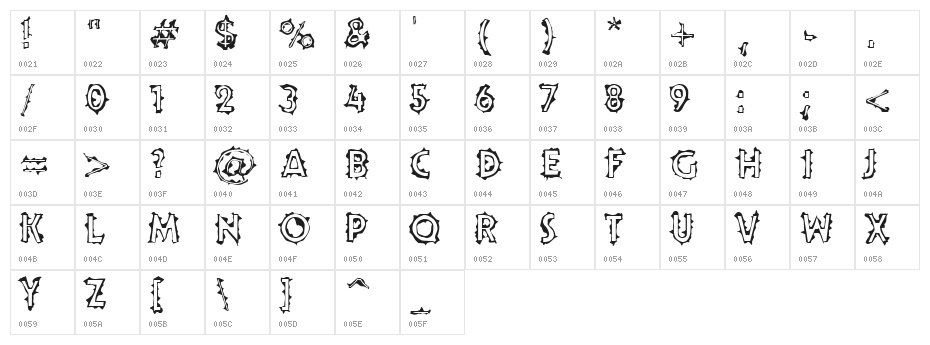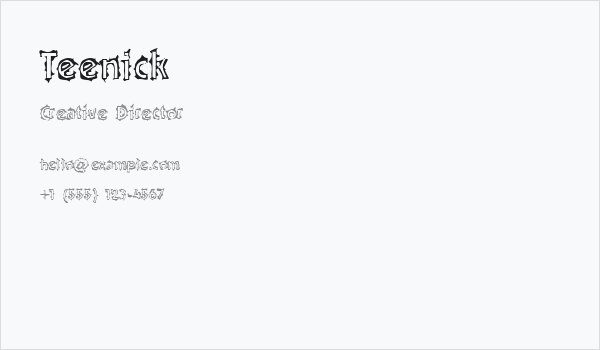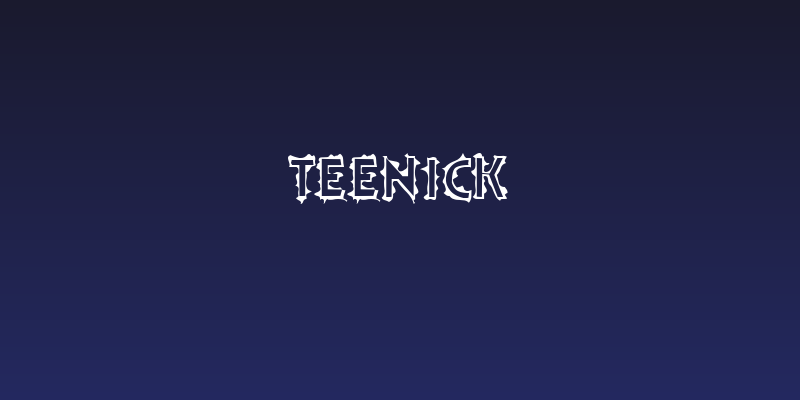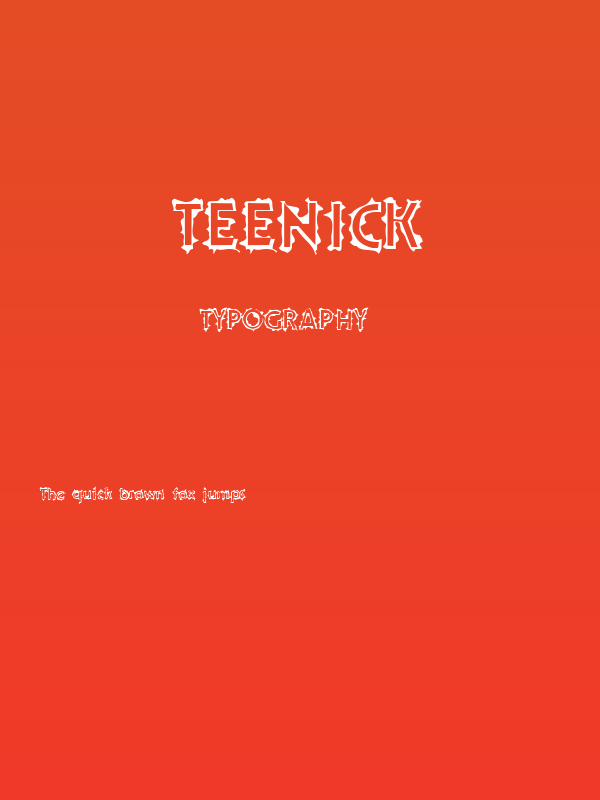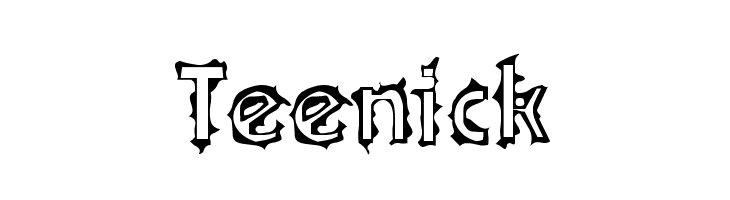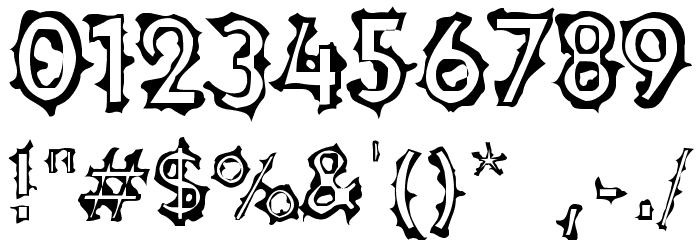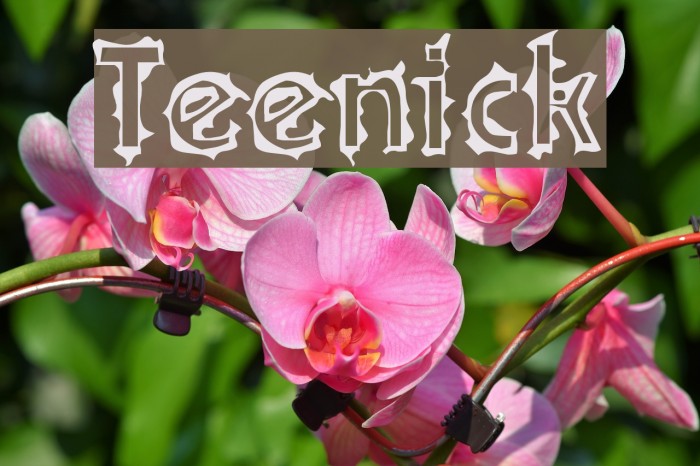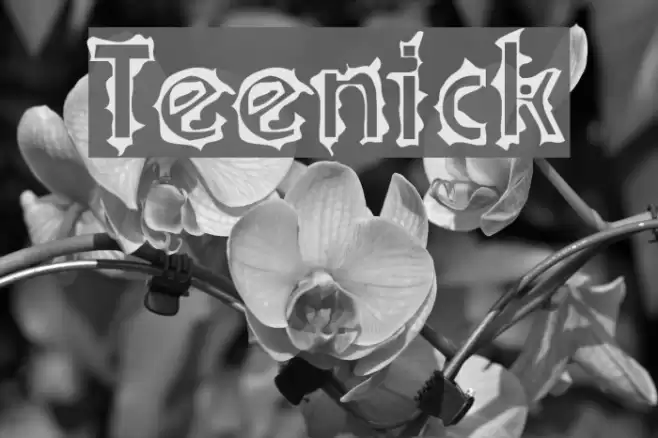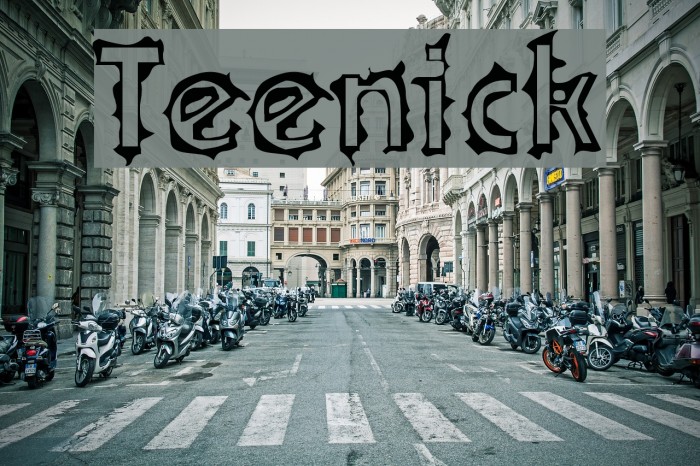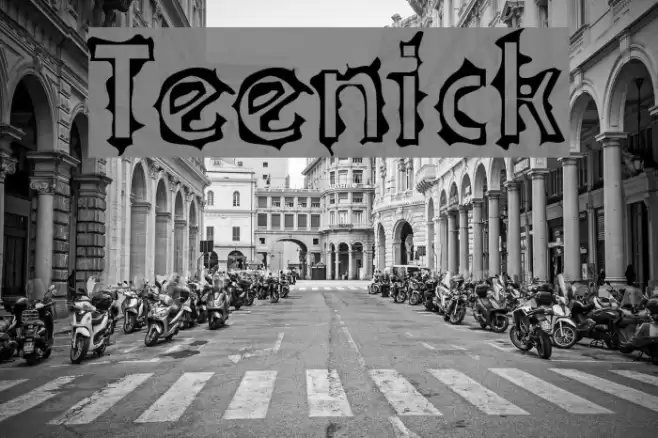
Teenick Font
| Style général | Modern, Edgy |
| Cas d'utilisation | Logos, Posters, Headlines |
| Projets proposés | Ideal for music album covers, skateboarding brands, graffiti art, and edgy fashion labels. |